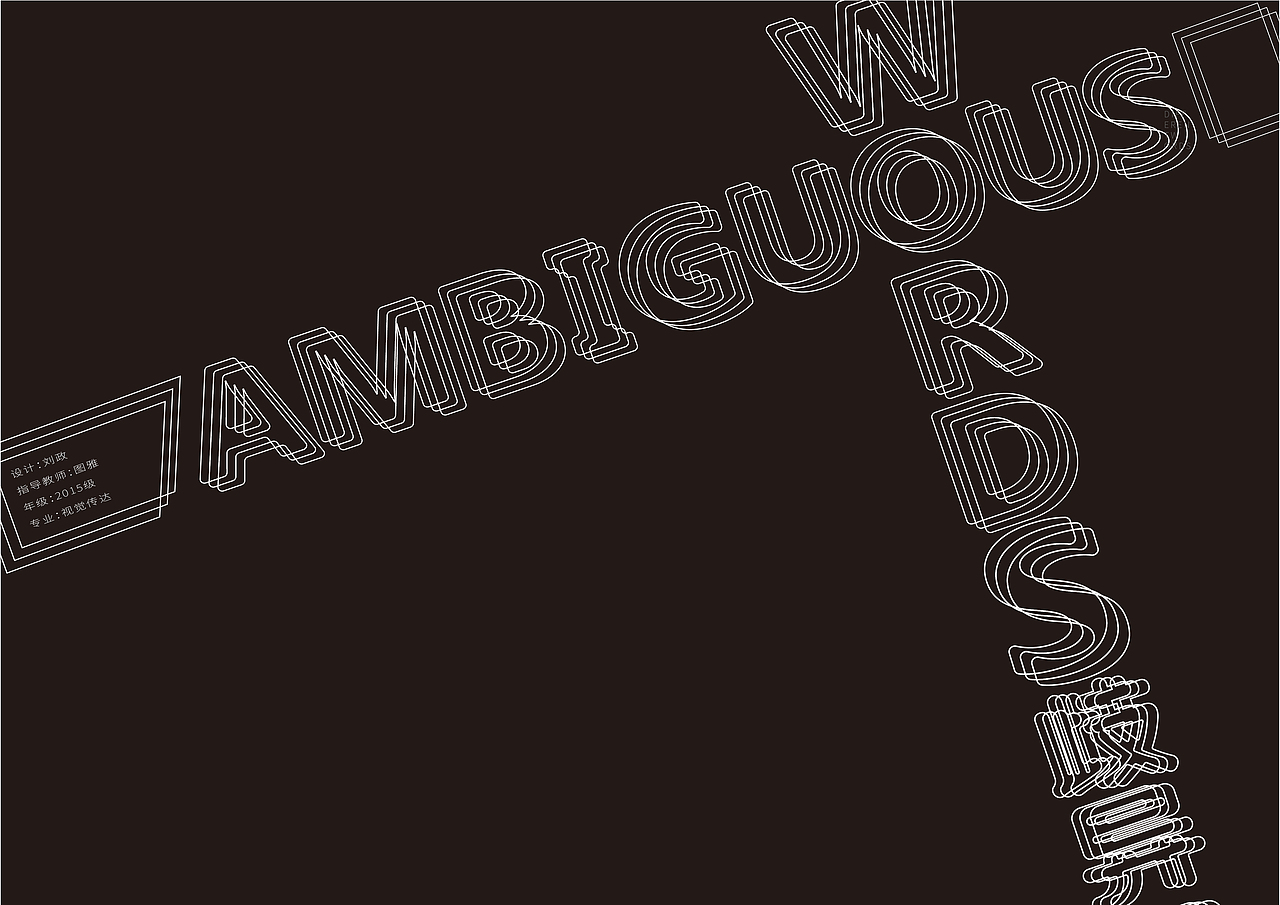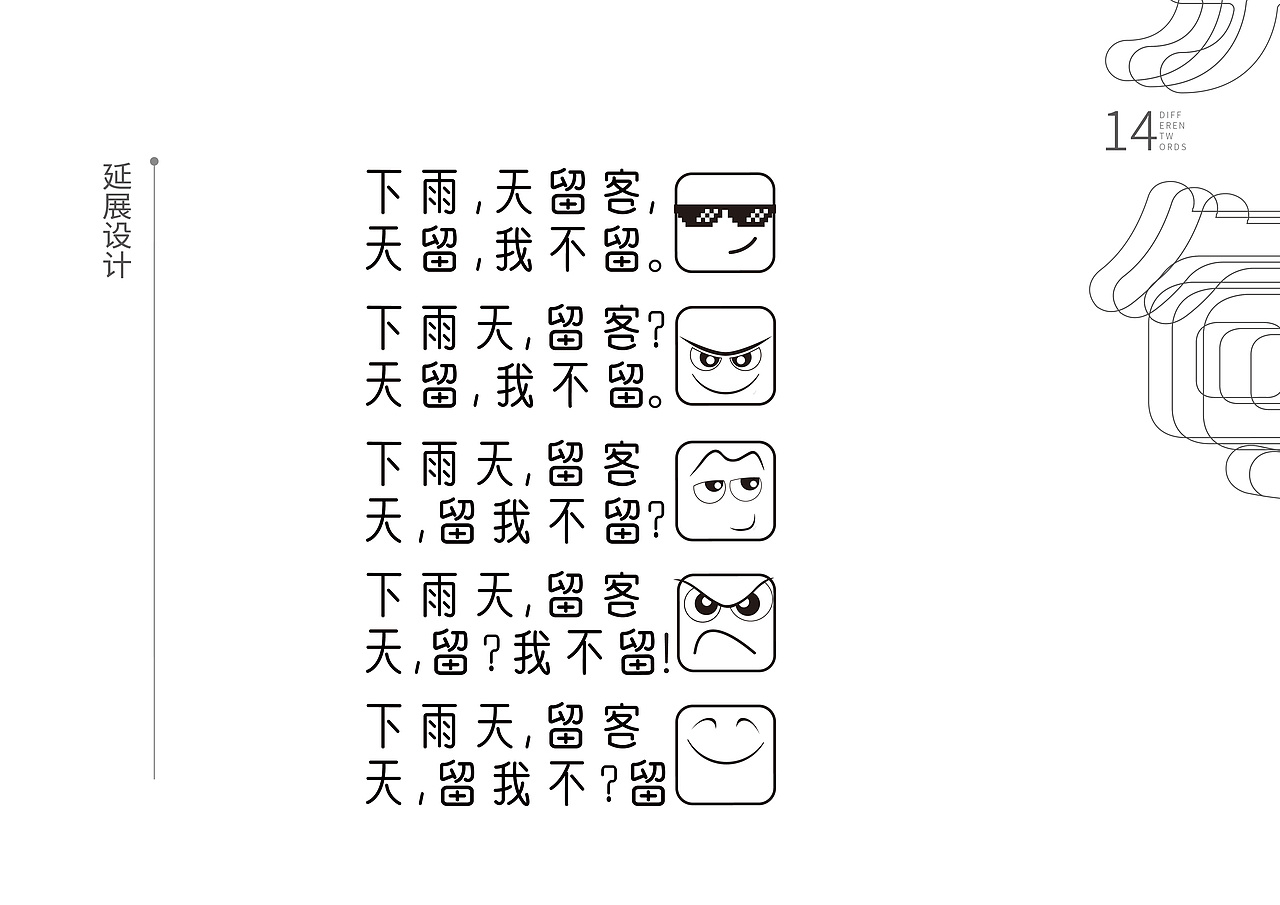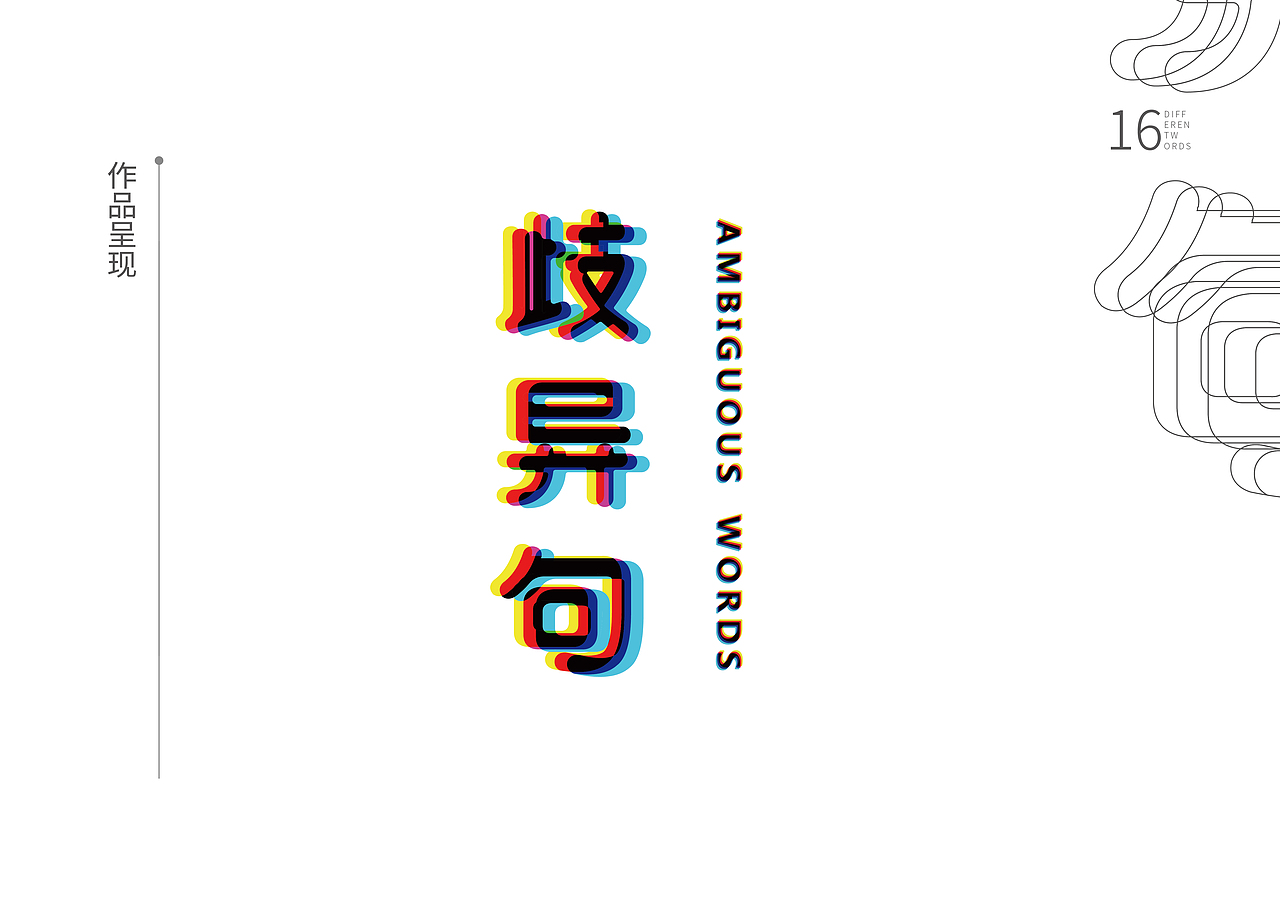
字体—歧异句(强烈建议缩放网页观看ctrl+鼠标中键)
学习汉语是当今潮流,然而汉语也是众多语言中最难的一种语言,同一个字在不同的表达中有着不同的概念、语法困难,一个音调的改变,可以改变整句话的意思、文言文,成语,诗,词,这些会让初学者抓狂。
毕设要用图片、颜色、排版方式以及文字的大小增强句子可读性,致力于用文字之外的元素改变句义。图形、文字、以及色彩等元素彻底把歧义矛盾打破,让受众能从歧义句中第一时间锁定语义。歧义句内涵丰富,表现从多个方面入手:配图形释义、换行、改变字体大小、增加字间距、插画释义、场景设定。
画布第一幅
画布第二幅
画布第三幅
画布第四幅
华容道,推动自和标点,句义随之改变
进度册
以下是毕业设计进展册